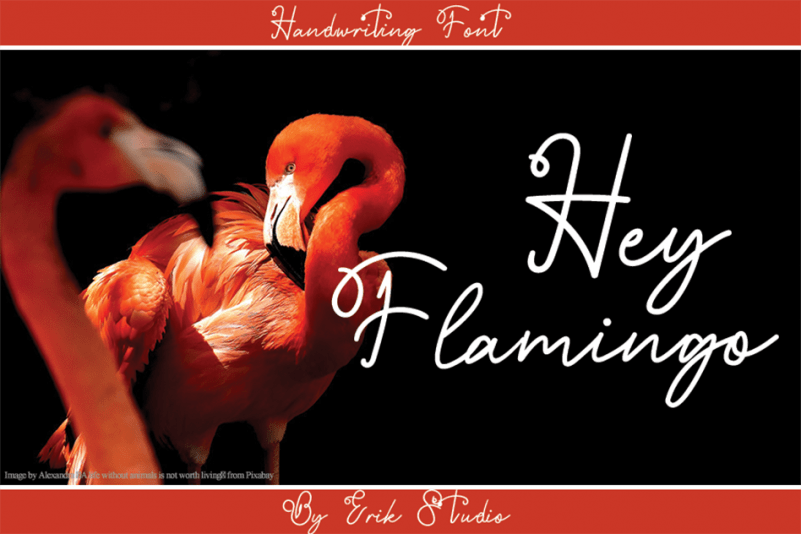
Hey Flamingo Handwritten Font – Download Grátis
Hey Flamingo Handwritten Font é uma elegante fonte escrita à mão que flui com suavidade e graça. Inspirada na delicadeza de escritores habilidosos, esta fonte perfeita para seus projetos pessoais permite que você crie designs impressionantes. Suas cores vibrantes e estilos únicos a tornam uma escolha única e atraente. Se apaixone por essa herança distintiva e eterna, ele se encaixa perfeitamente em qualquer design. Este é mais do que apenas uma fonte; é uma paixão para seus projetos pessoais.